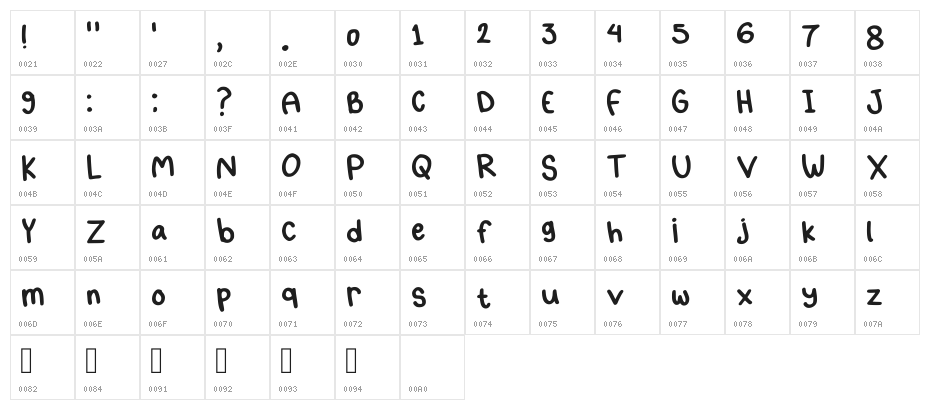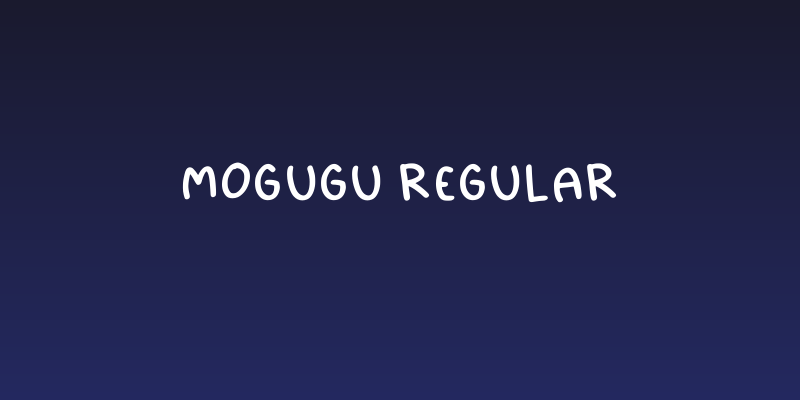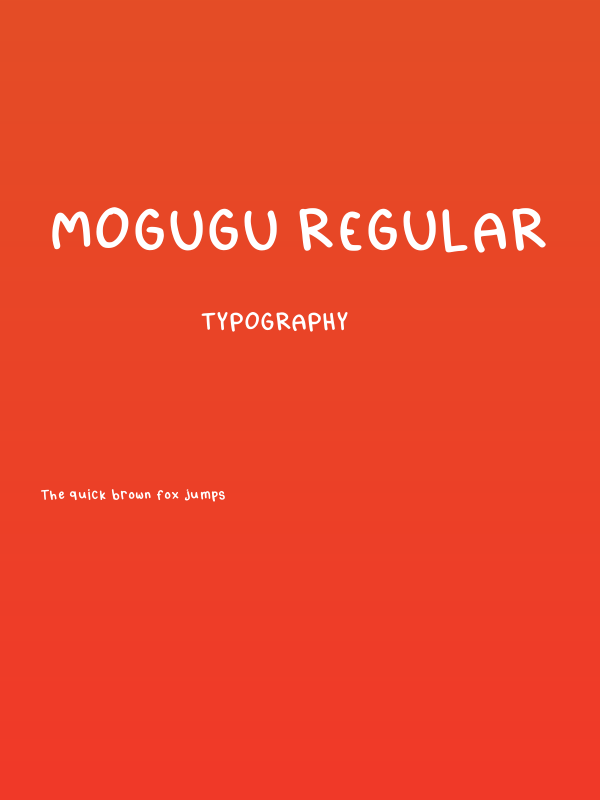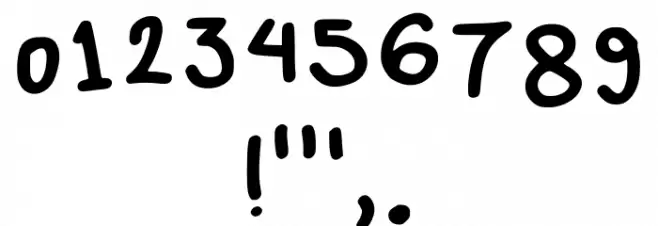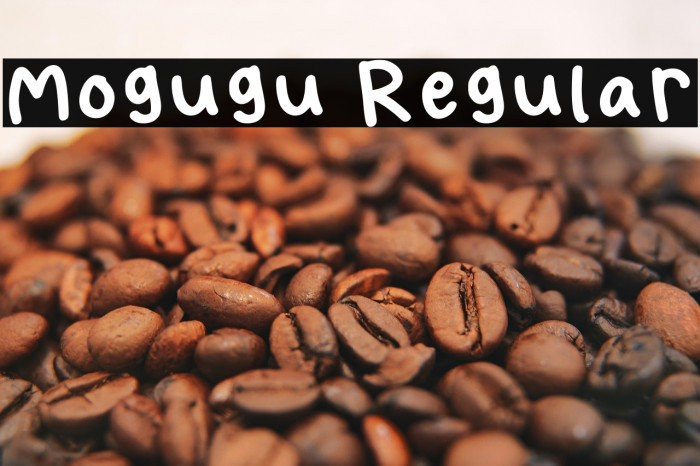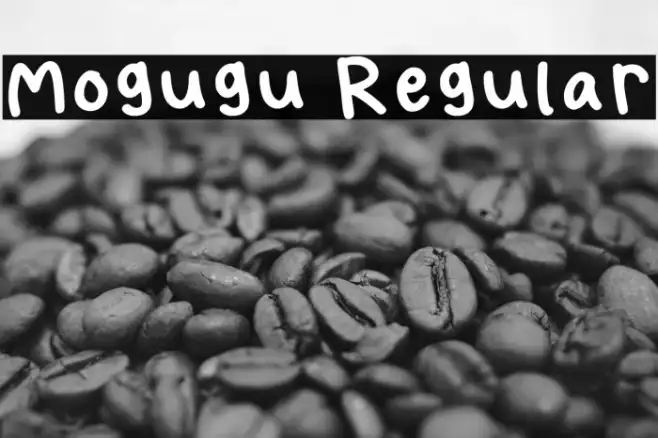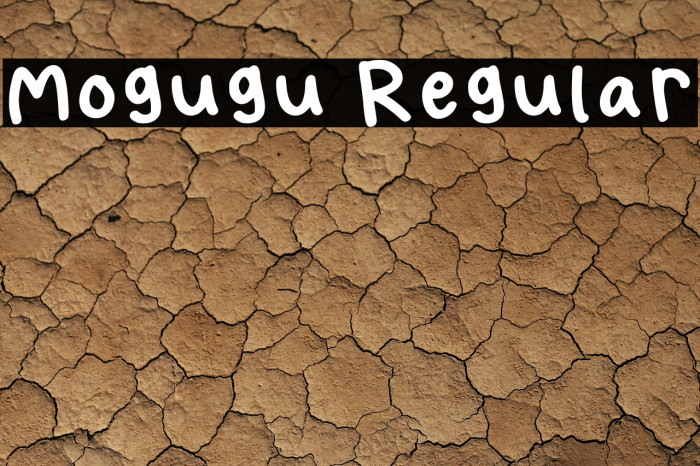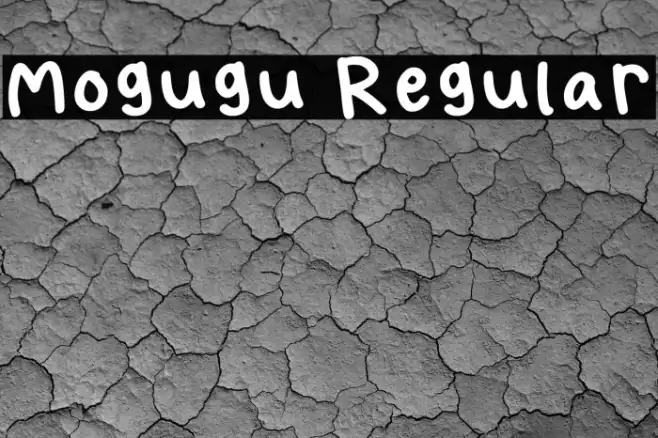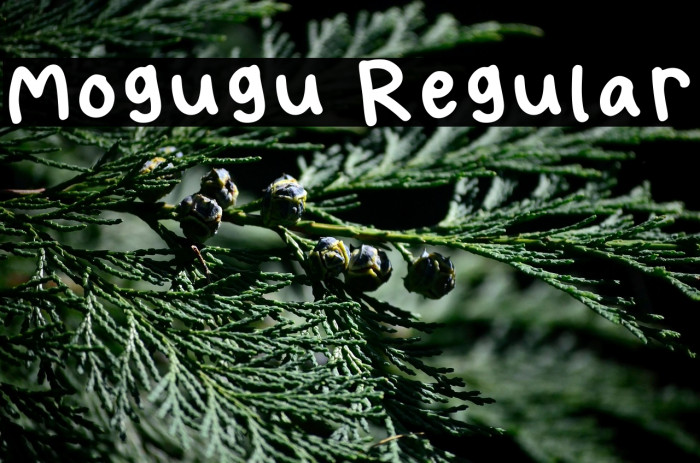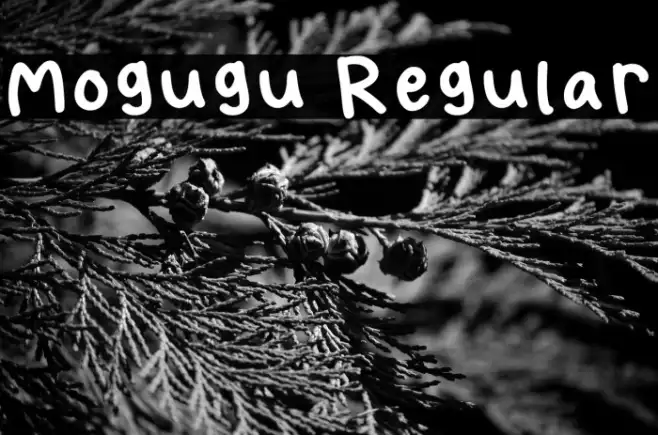
Mogugu Regular Font
| Gesamtstil | Playful |
| Anwendungsfall | Logos, Headlines, Informal Text |
| Vorgeschlagene Projekte | Ideal for children's books, greeting cards, playful branding, and informal invitations. |